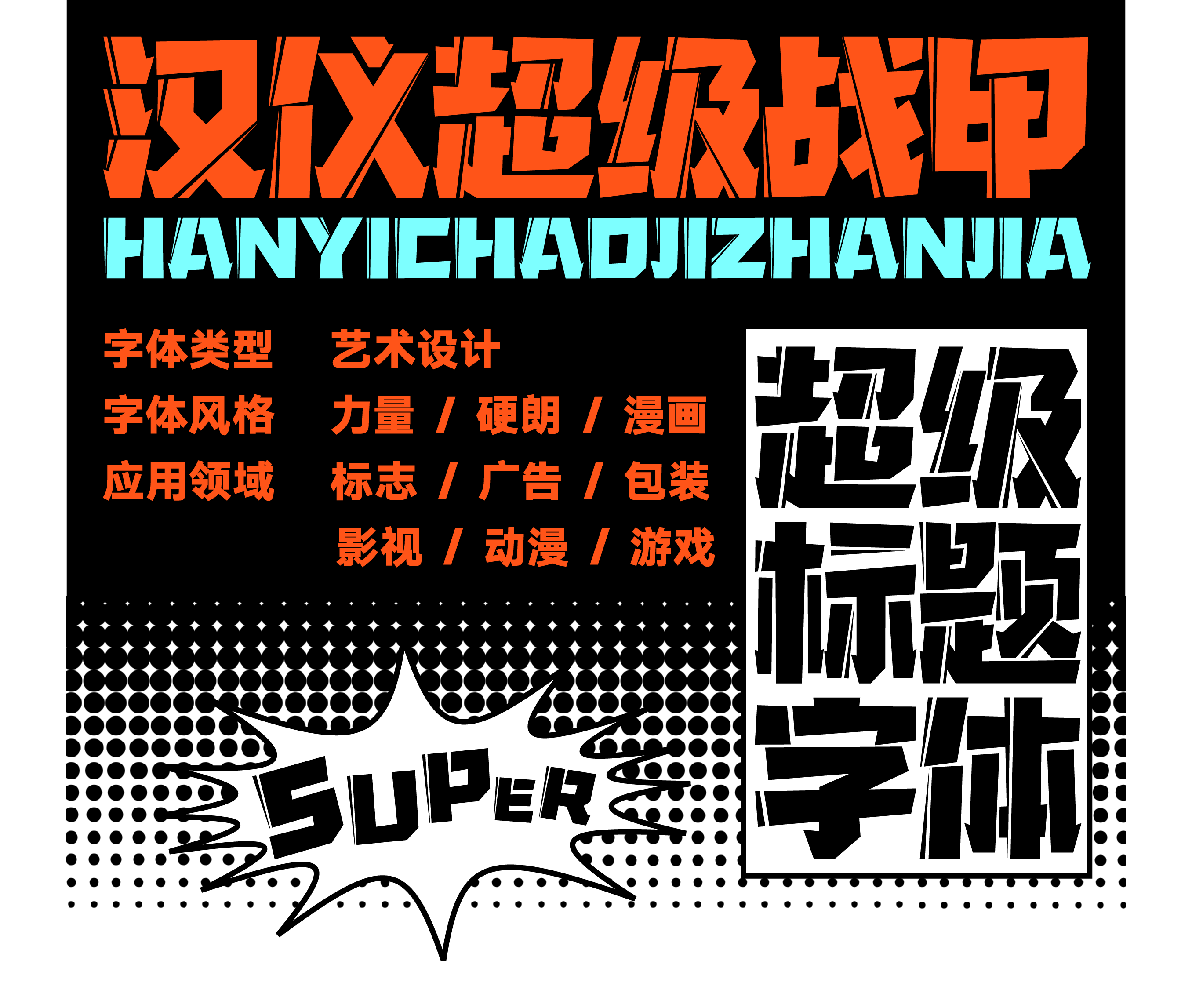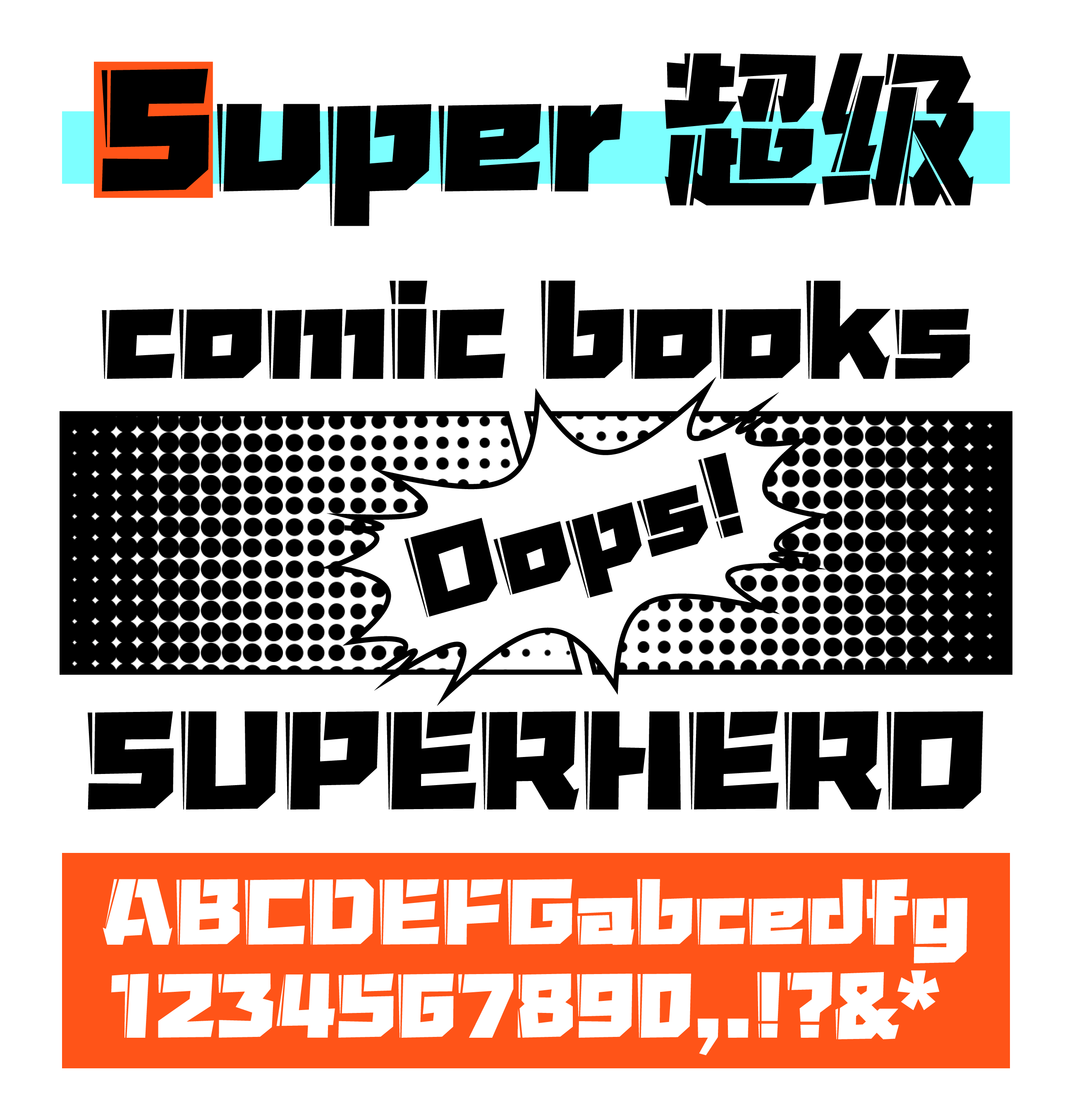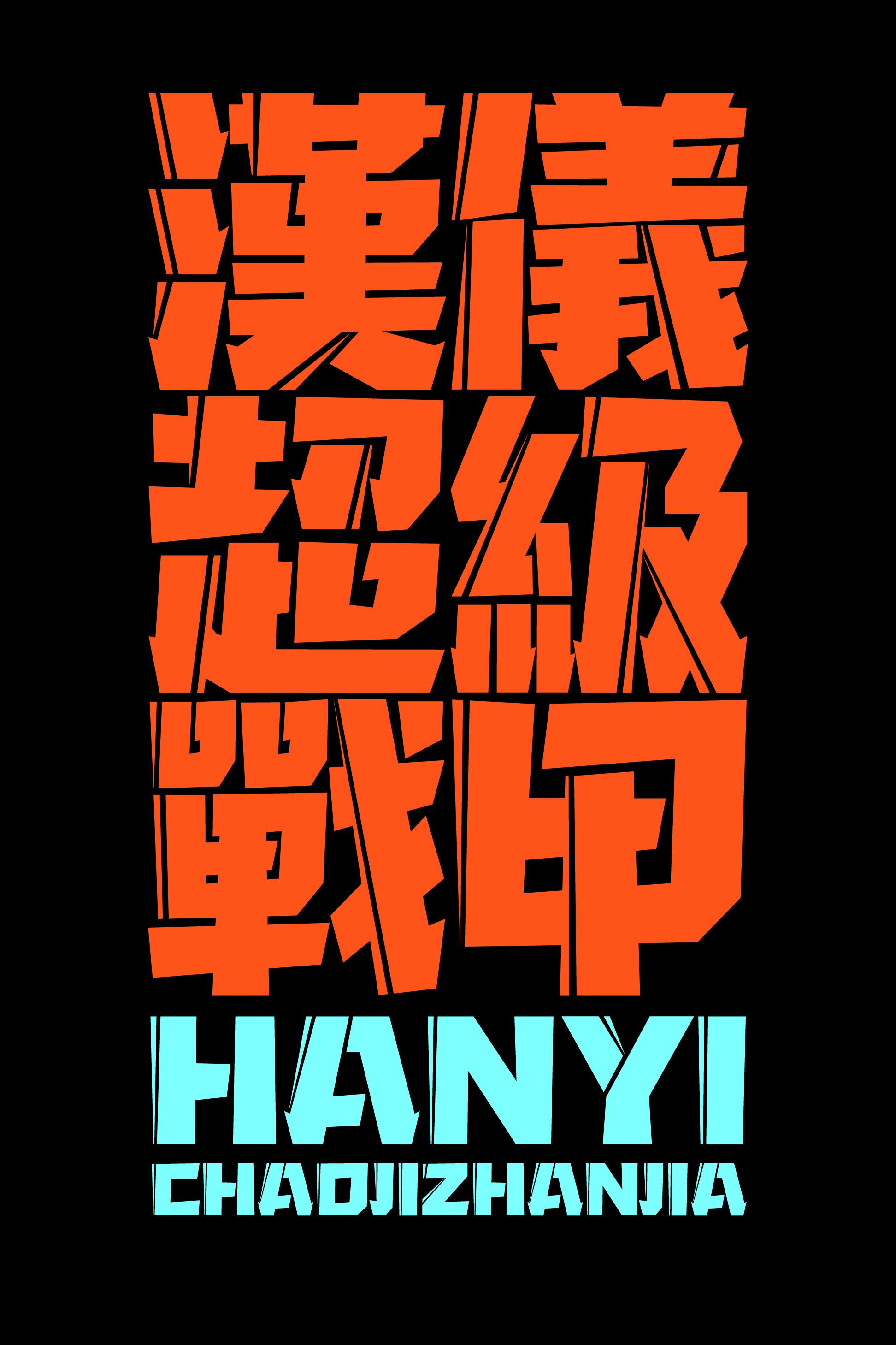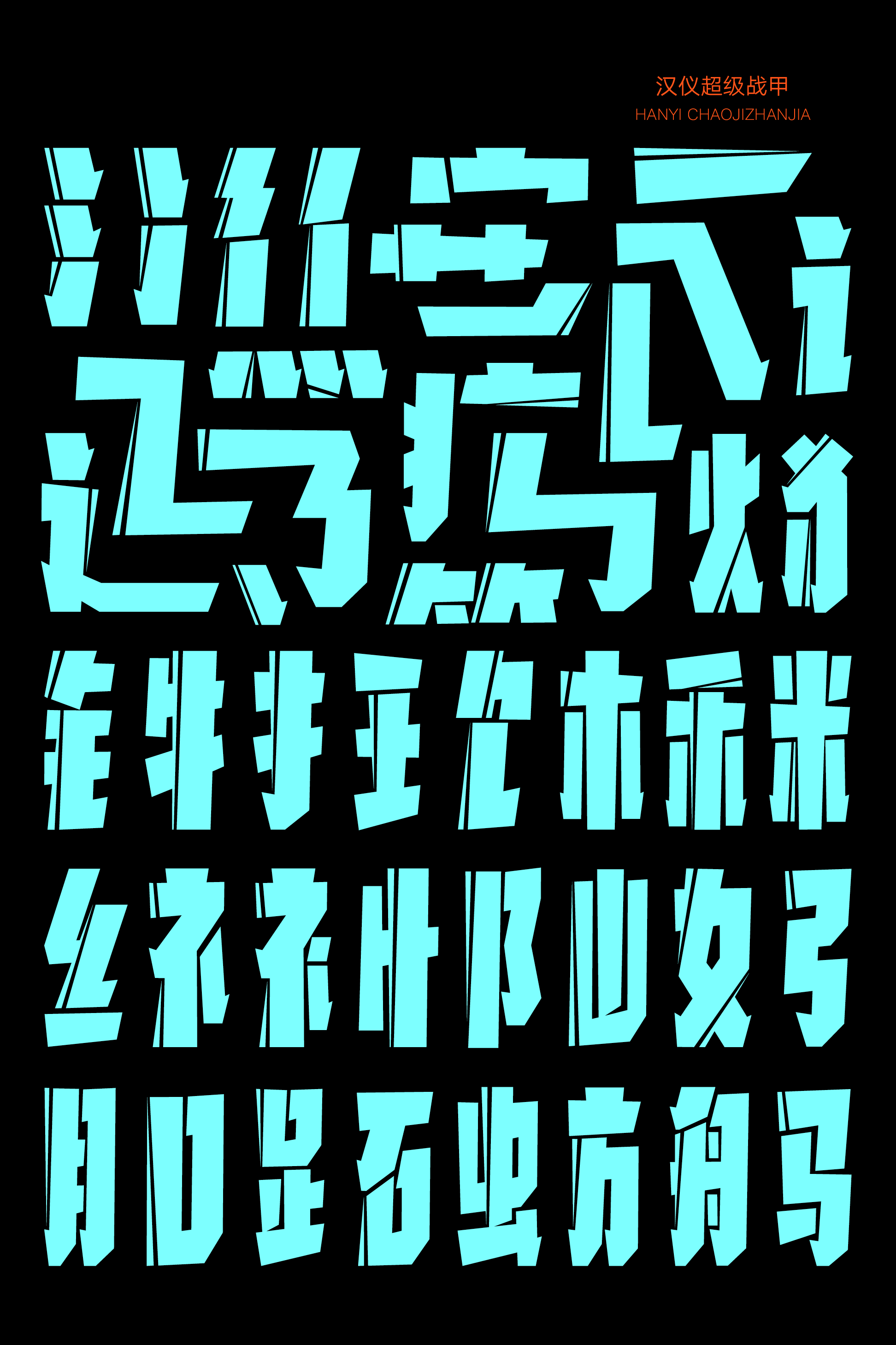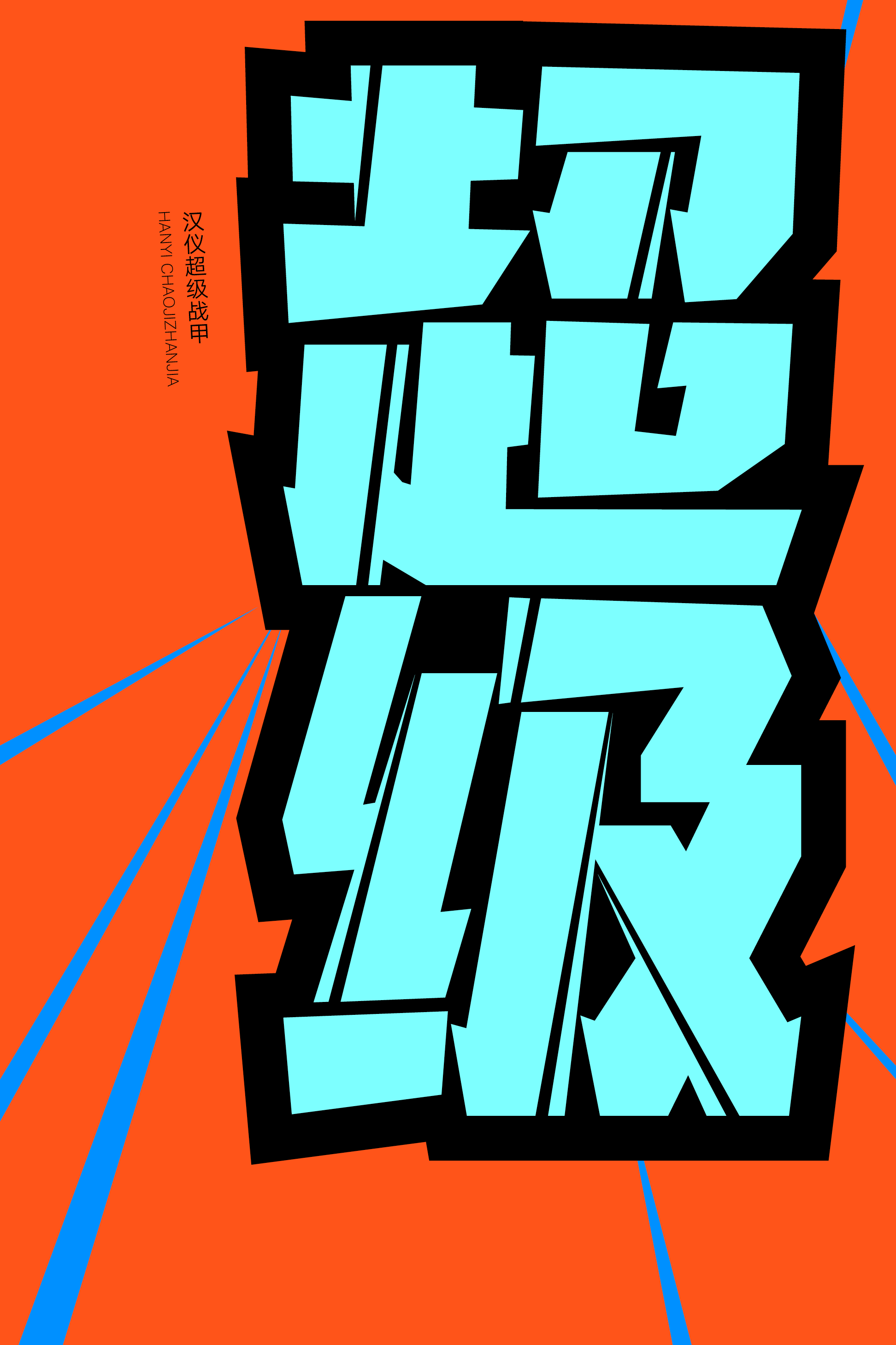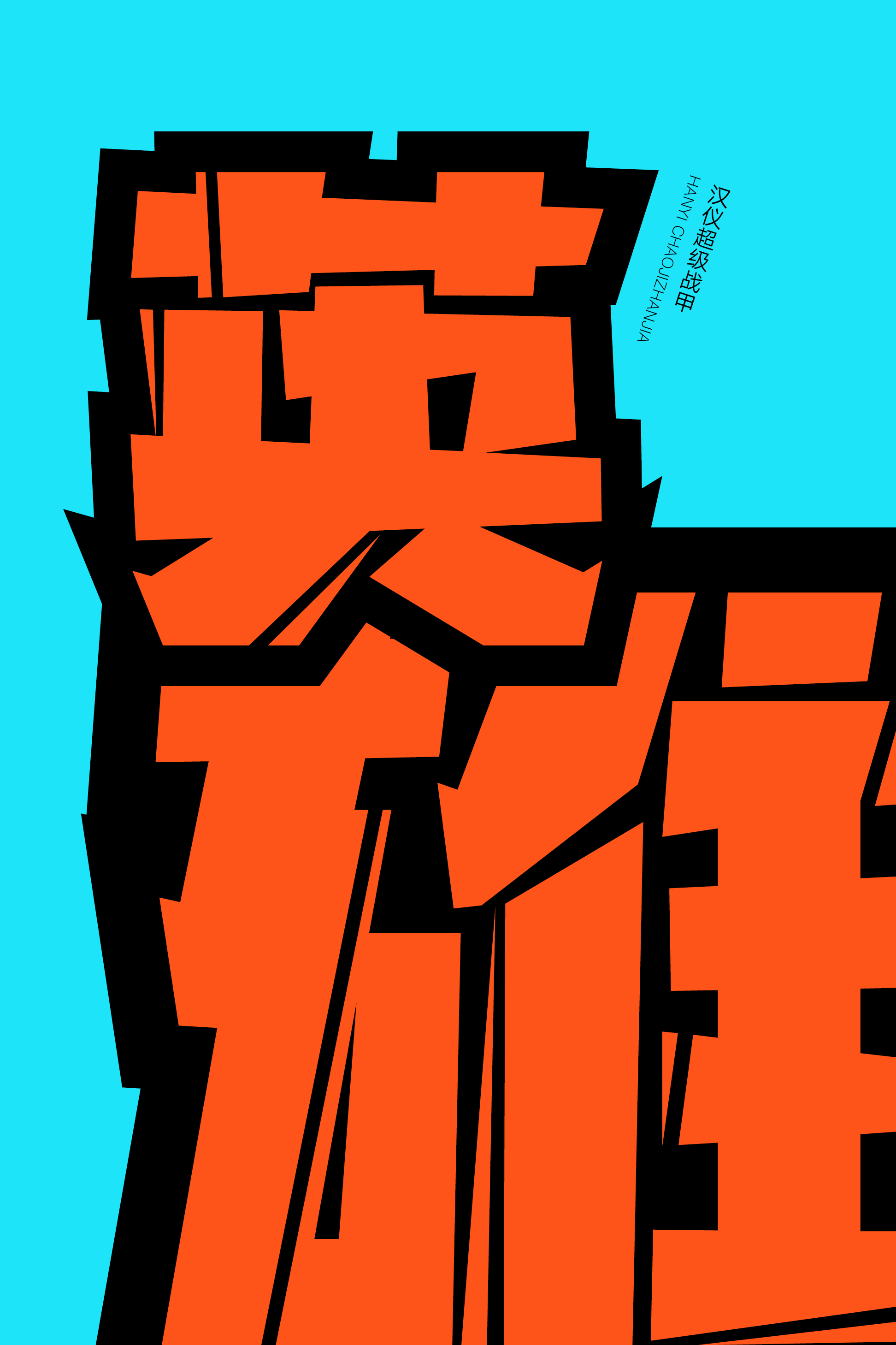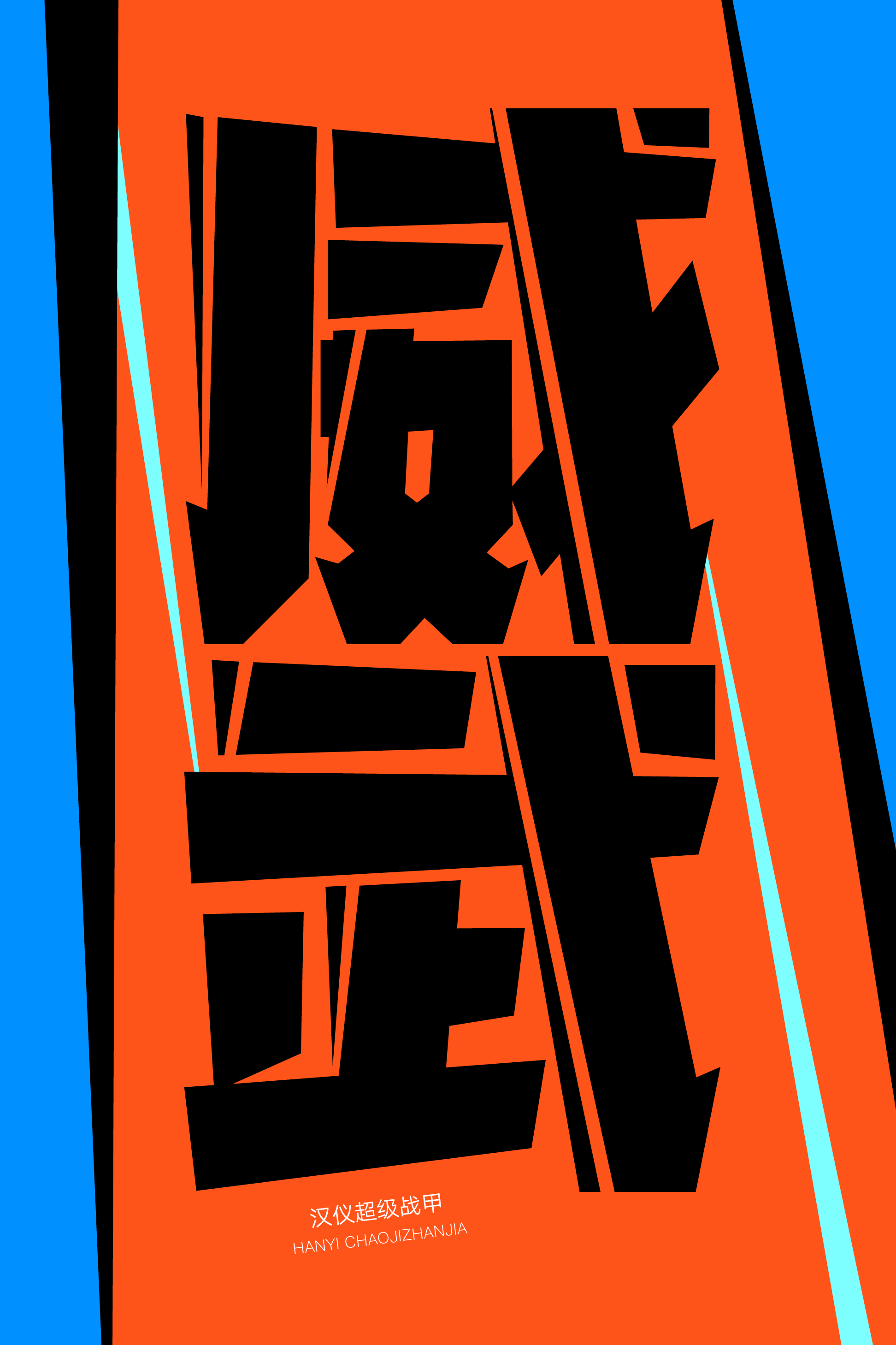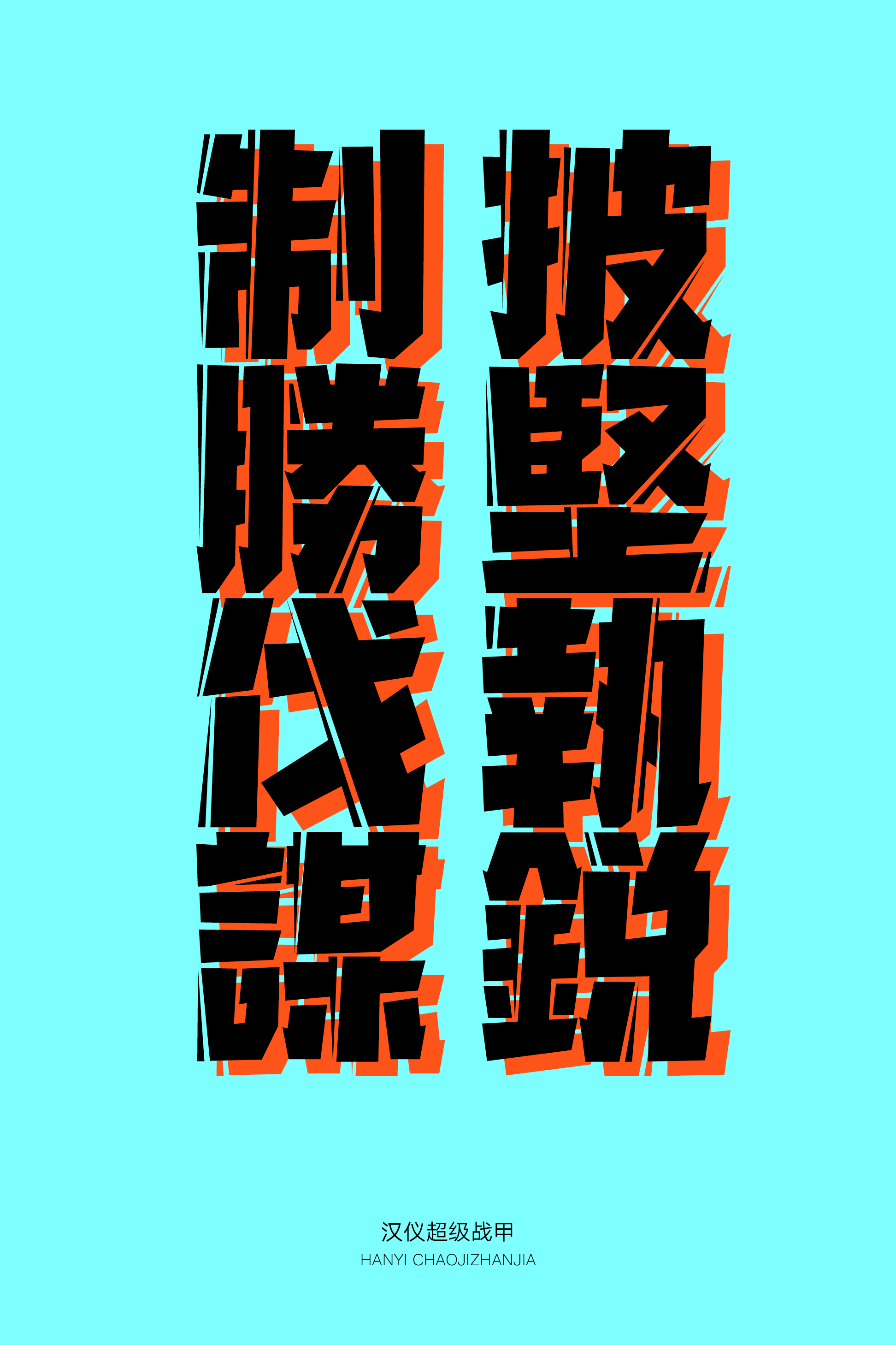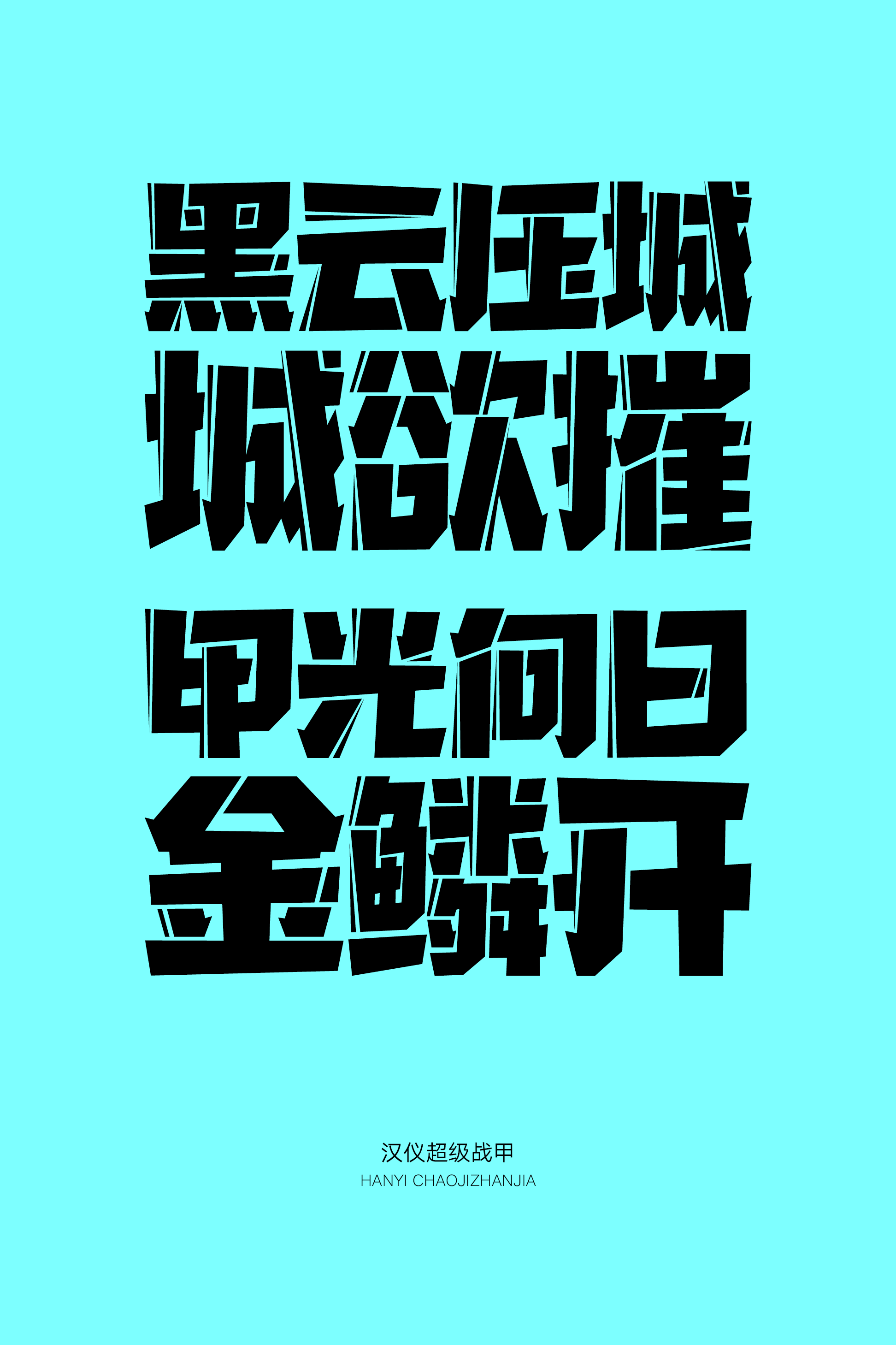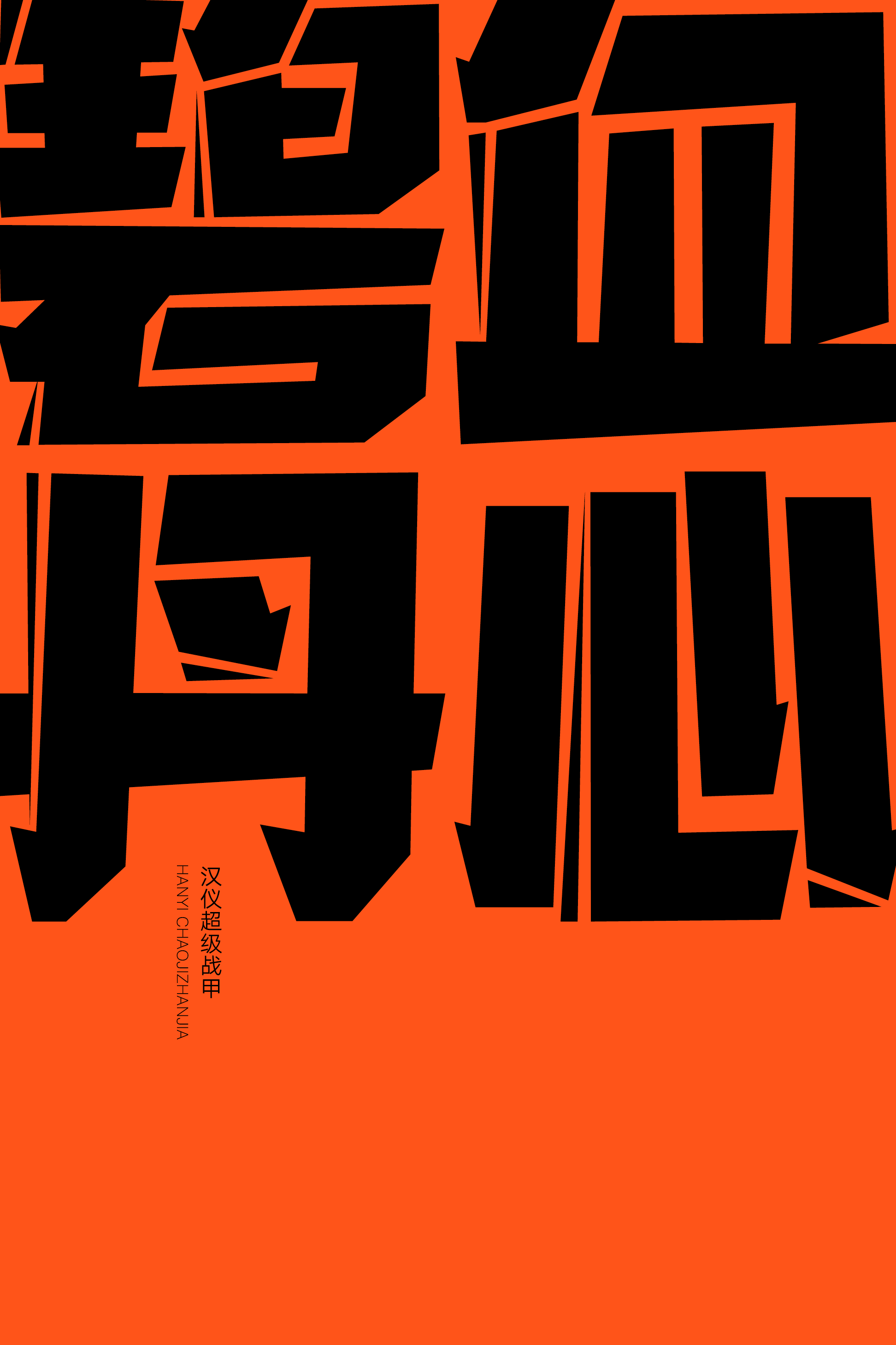
汉仪超级战甲
超级标题字体——汉仪超级战甲,重磅登场!这是一款极黑的重量级标题字体,方块的造型极具力量感,全直线的构成霸气硬朗,锐利的笔画断裂装饰渲染了强烈的漫画风格。汉仪超级战甲,字如其名,带来战甲般的超级视觉冲击力,适合作为标题字体应用于游戏动漫、动作及科幻类电影、广告包装等使用场景。
极黑的方块造型充满力量感。
笔画由全直线构成,霸气硬朗。
粗细变化、左右倾斜,呈现出速度感。
锐利的笔画断裂装饰带有强烈的漫画风格。
西文部分同样是全直线构成极黑的方块造型,加入笔画断裂装饰,中西文匹配即是撕开漫画的视觉冲击感。